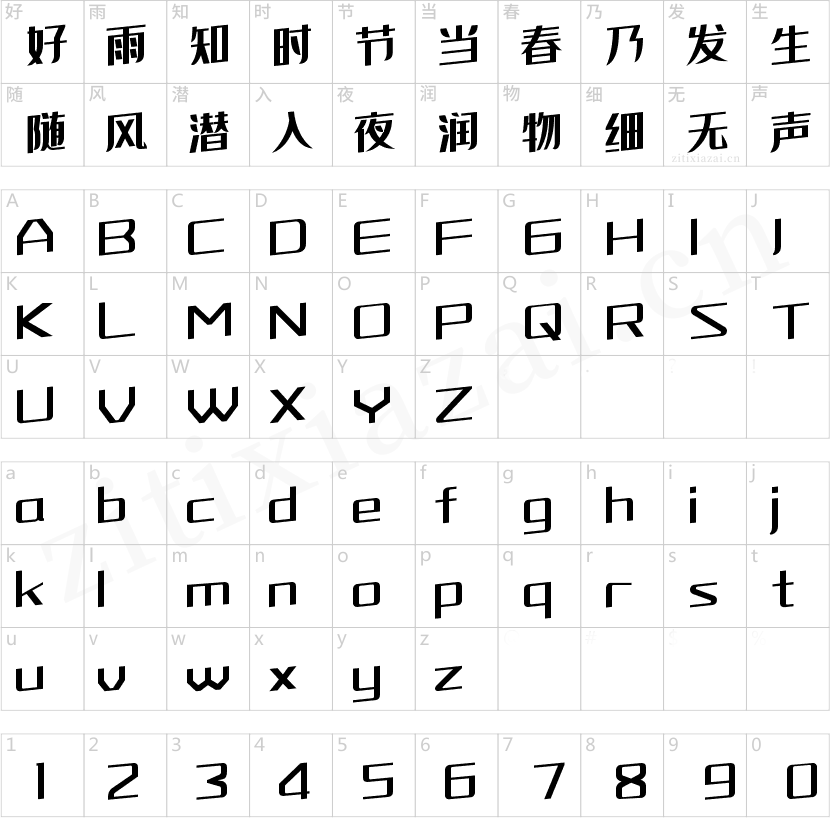
字魂跨界黑
字魂跨界黑,这款字体结构工整、笔画清晰,兼顾美观与易读性,适用于标题、正文、海报、包装、LOGO 等多种场景。字形优雅稳定,风格百搭耐看,适配日常排版与创意设计,让文字呈现更舒适、更具质感。字魂跨界黑一笔一画,皆是细节,以均衡的比例、流畅的线条打造舒适视觉体验,字形端正大气,风格简约现代。无论是商业设计、品牌宣传还是日常排版,都能轻松驾驭,让文字更有格调与力量。字魂跨界黑字体下载。
字魂字体字魂跨界黑字体是由字魂创意字库设计并生产的一款可商用的字体,被收录于字魂先锋系列。该字体支持GB-2312标准,包含6913个中文、字母、符号和数字,字体类型偏向黑体,具有活泼、中国风的风格,在市面上广泛用于包装印刷、排版阅读、党政公务等场景。